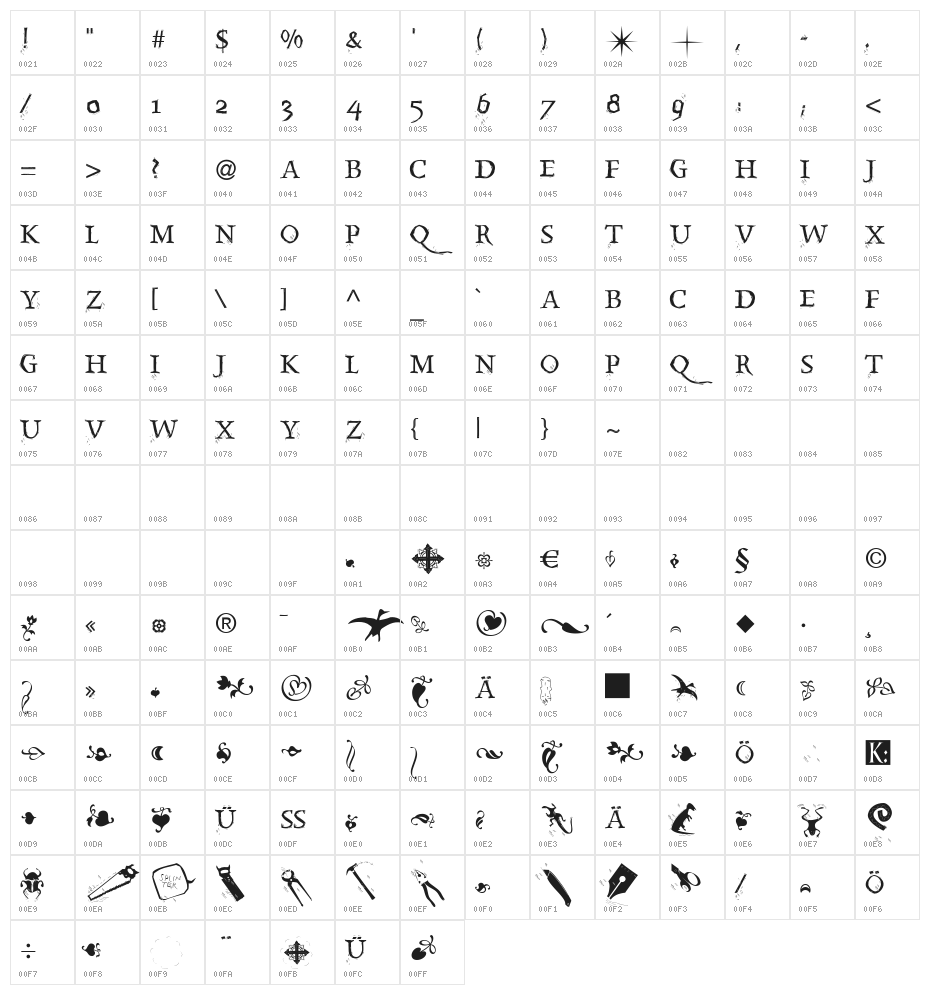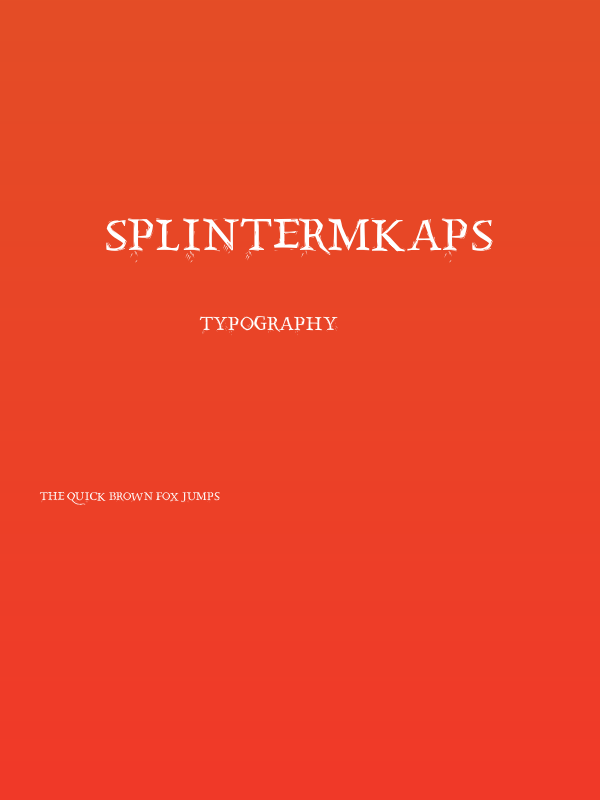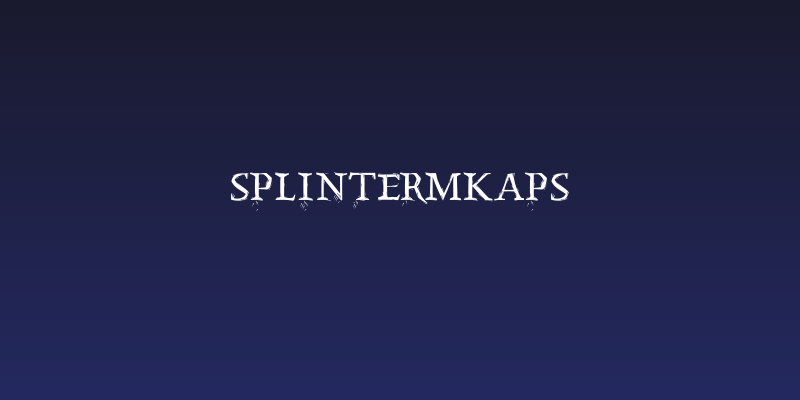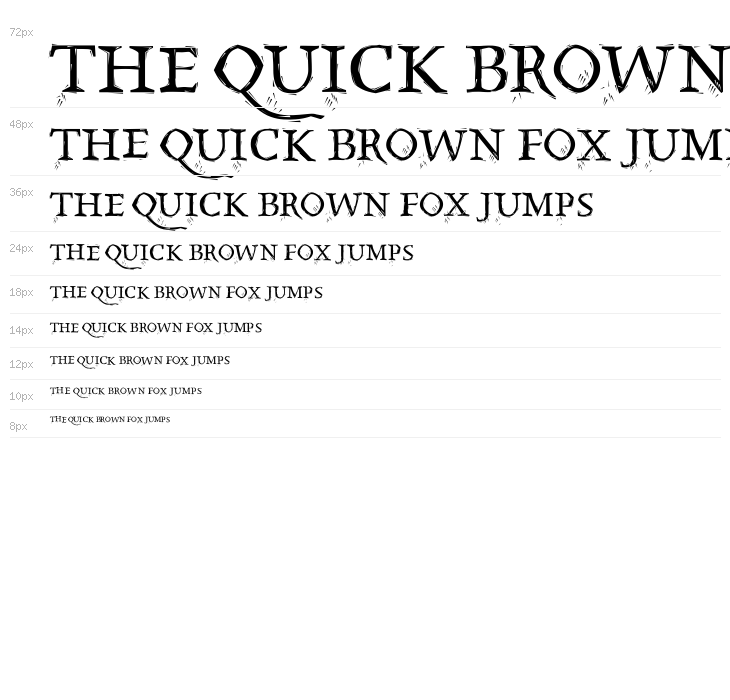
SplinterMKaps Font
| 全体的なスタイル | Modern, Edgy |
| おすすめプロジェクト | Ideal for album covers, posters, video game graphics, and any project needing a bold, edgy aesthetic. |